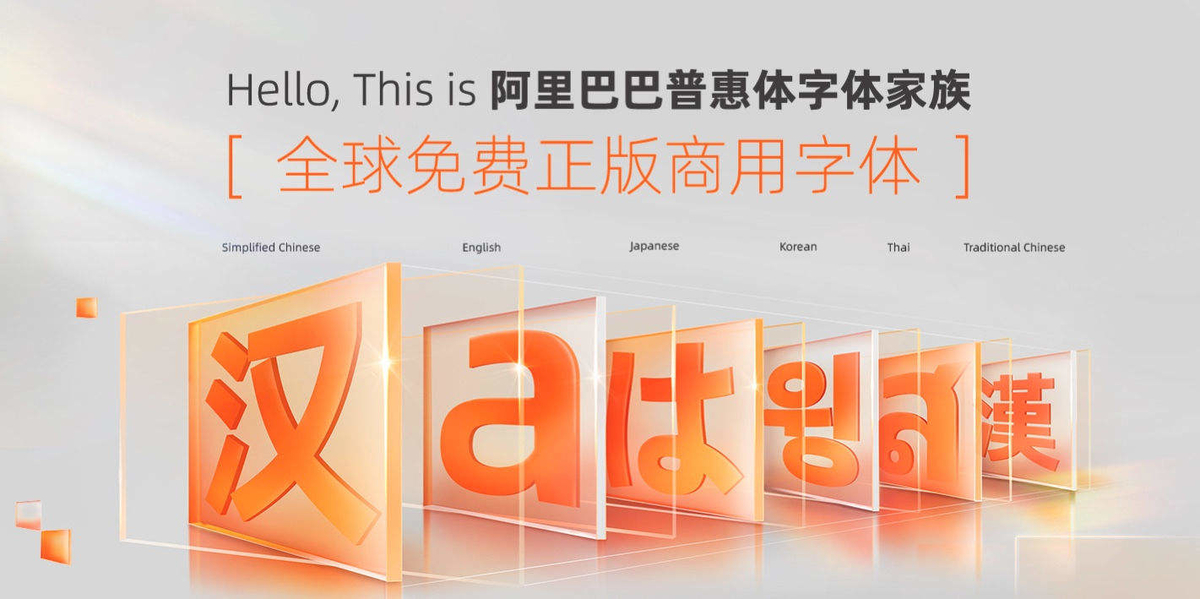
アリババが商用可能なフリーフォント「Alibaba Sans」の派生フォントを拡充、フォント著作権確認ツールも提供
アリババは2022年8月12日(金)に400万回以上ダウンロードされている人気フォント「Alibaba Sans」に新たな派生フォントを追加したことを発表した。
派生フォントは、日本語を含む多言語に対応し、プライベートでも商業目的でも無料で利用することができる。
アリババが今回発表したのはカスタムデザインされた新たな「Alibaba Sans」 派生フォント。
中国語(繁体字)、日本語、韓国語に対応し、プライベートでも商業目的でも自由に使用できる。
こちらは、年に一度、クリエイティブ業界の専門家らが集まり、4日間にわたる展示やパネルディスカッションが開催される「U Design Week」で発表された。
アリババグループでは2019年に中国企業として初めて無料で商用利用できるフォント「Alibaba Puhuihui」を発表。
その後、2021年5月には、「Alibaba PuHuiTi 2.0」をリリースし、従来の中国語(簡体字)と英語フォントの一部を改良しただけでなく、新たにタイ語とベトナム語などの外国語フォントを追加した。
提供開始から4年半で、「Alibaba Sans」フォントは派生フォントを含め400万回以上ダウンロードされている。